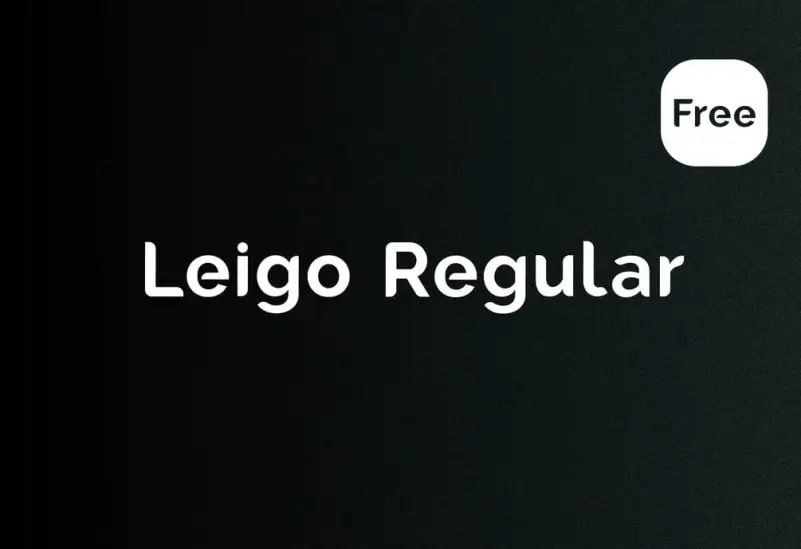
Leigo Regular é uma fonte elegante mas despojada, perfeita para qualquer projeto que você esteja planejando. Criada pelo designer Hamilton, essa fonte moderna e clássica foi projetada não apenas para o uso estético, mas também para se adaptar em várias aplicações gráficas. Uma das características mais distintivas de Leigo Regular é sua forma arredondada, que faz com que os caracteres pareçam serim traçados manualmente por canetas. Esta característica torna-a perfeitamente adequada para uma ampla gama de projetos visuais, desde a criação de logotipos e rótulos de embalagem até ao design de flyers ou capas de produtos. A sua versatilidade e estilo único garantem que Leigo Regular será um aliado valioso no seu próximo projeto visual, seja na criação de branding ou em qualquer outro uso de texto em estilos digitais.